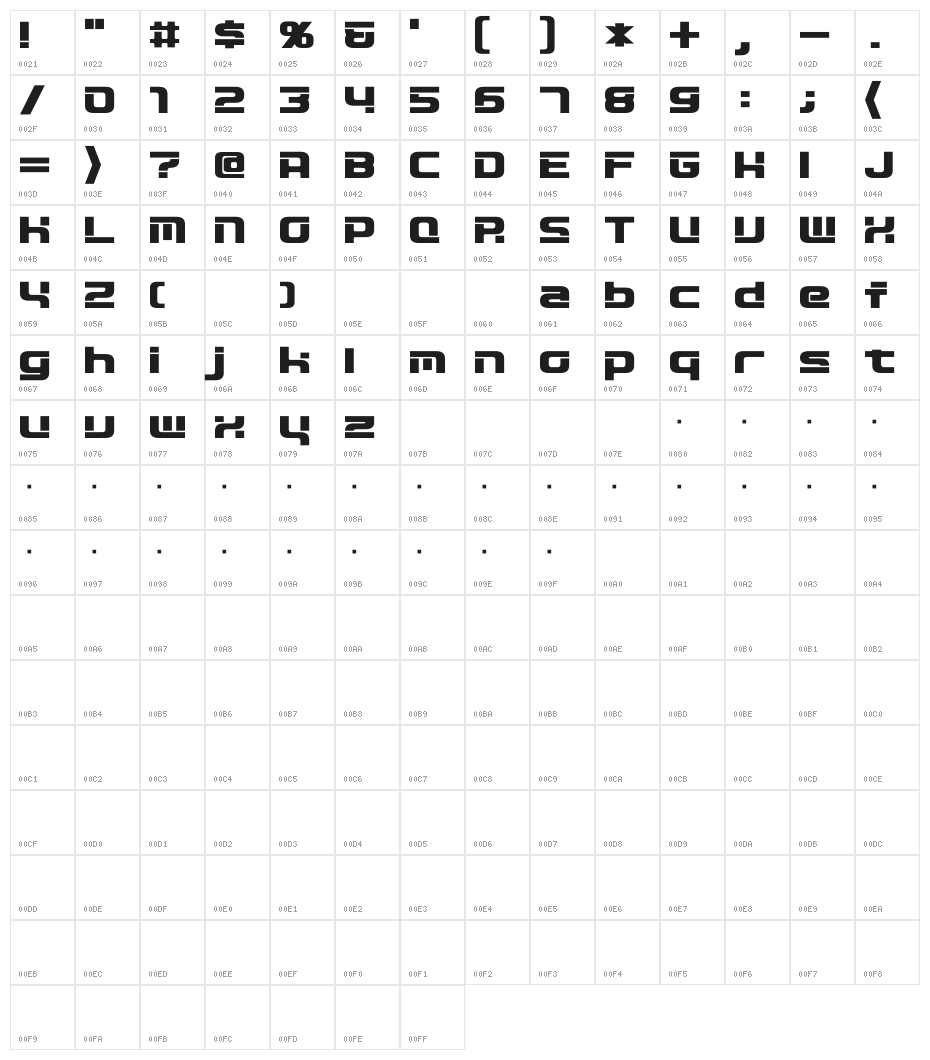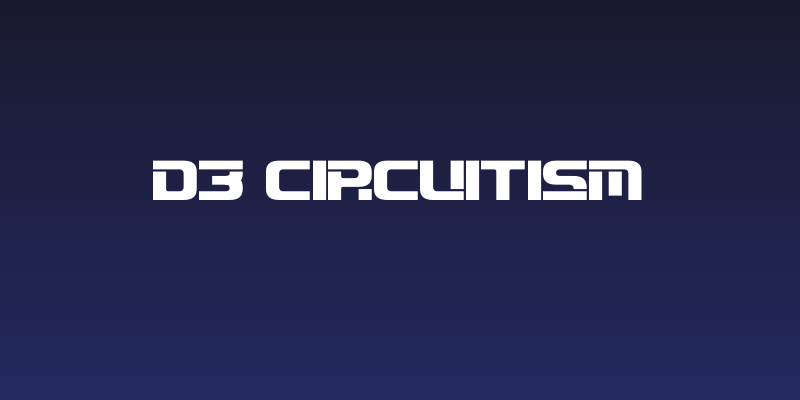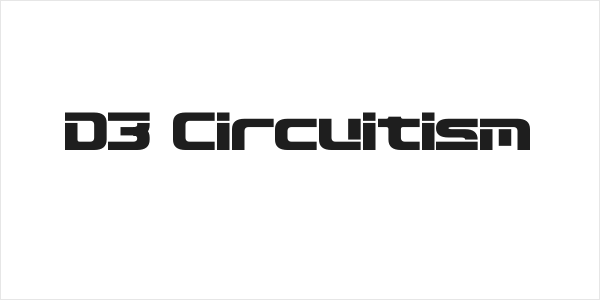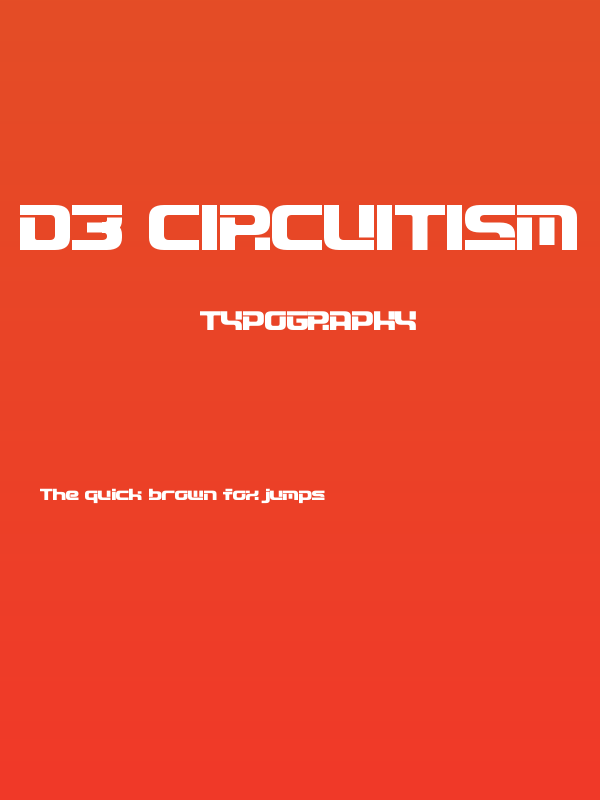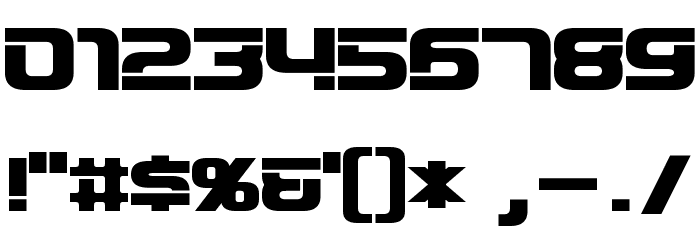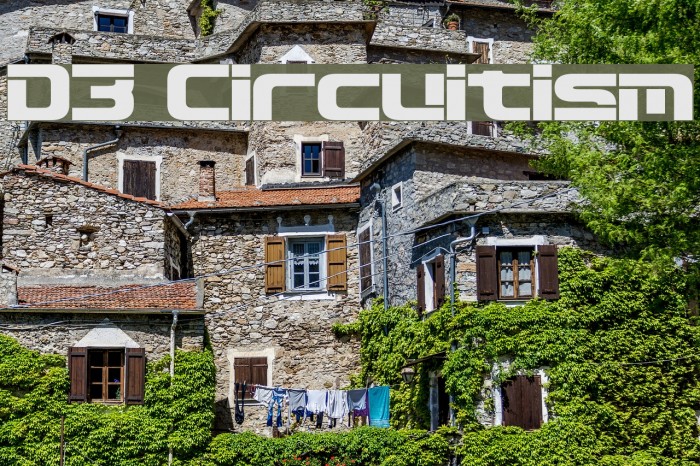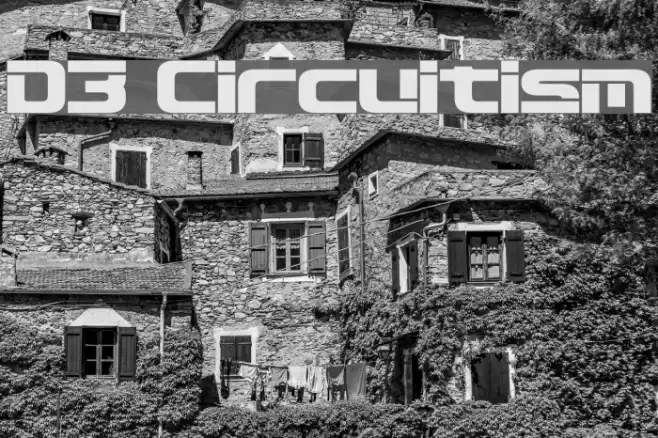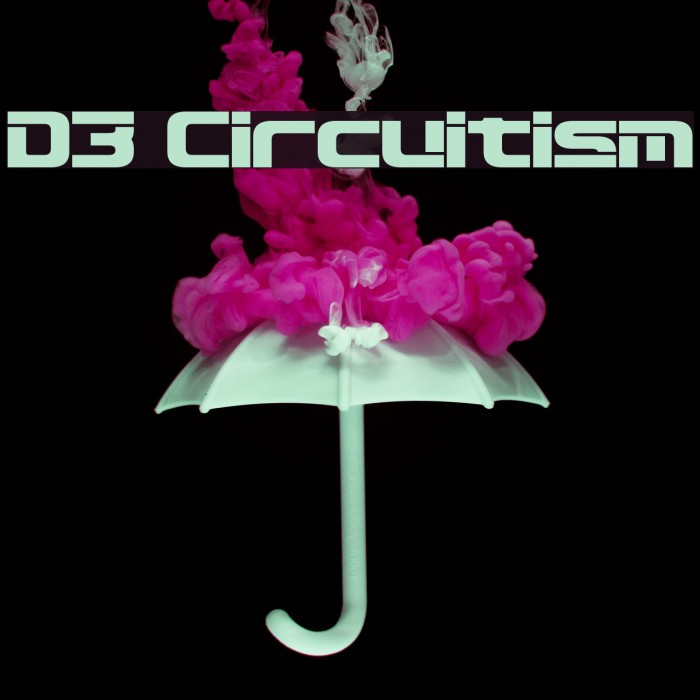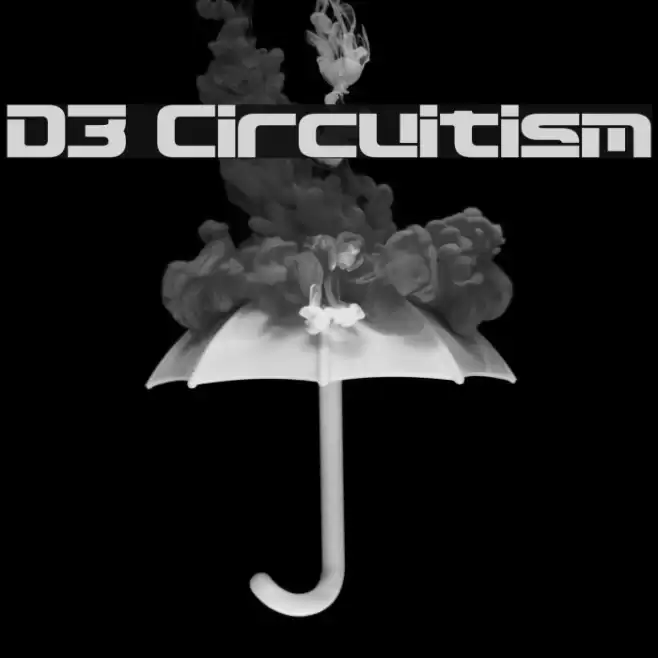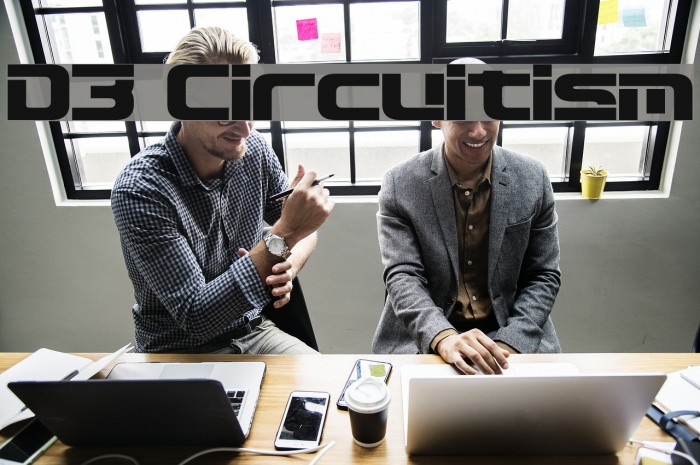
D3 Circuitism Font
✎ Futuristic
| Vorgeschlagene Projekte | Ideal for technology branding, video game titles, sci-fi movie posters, and digital interfaces. |